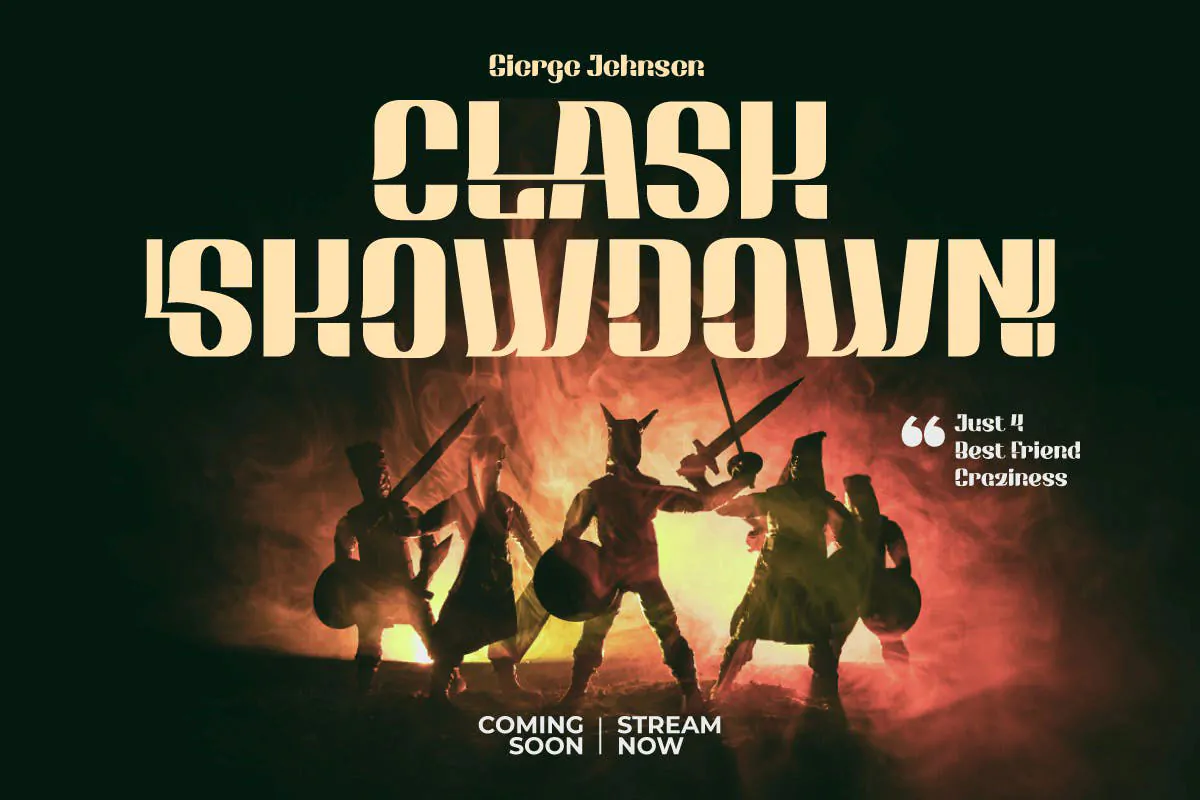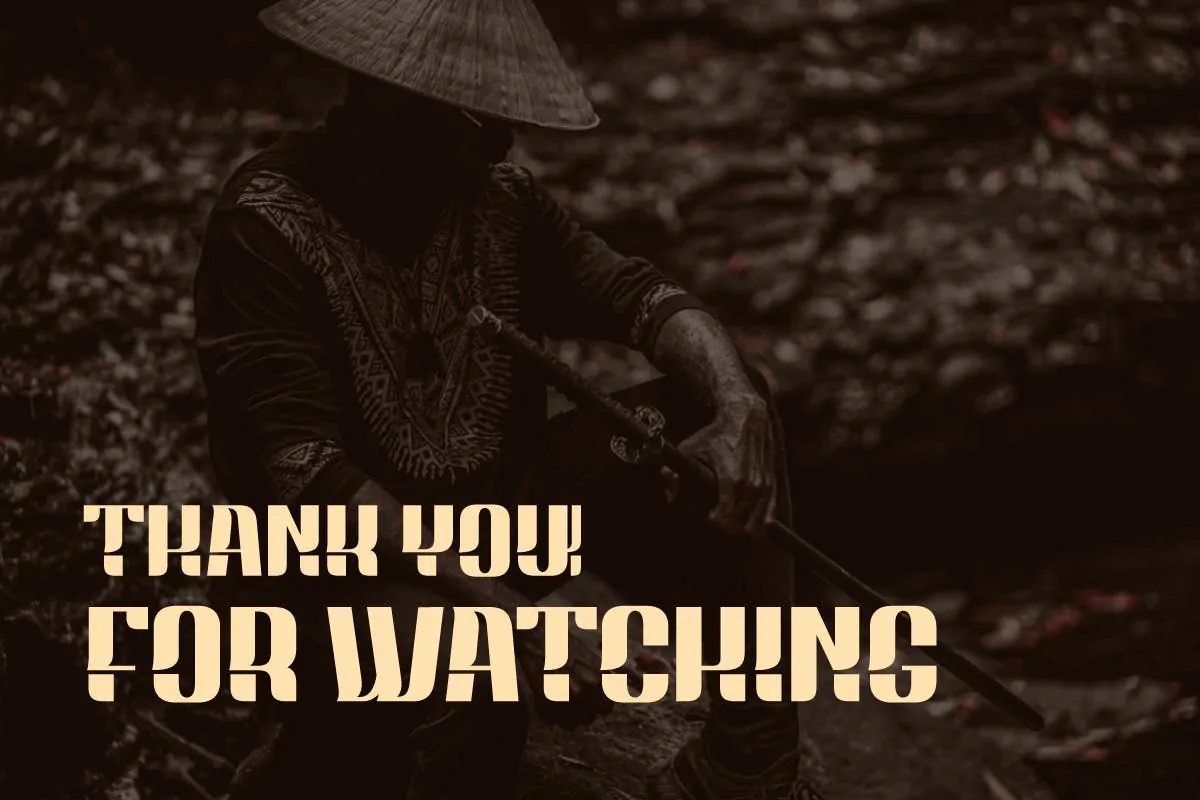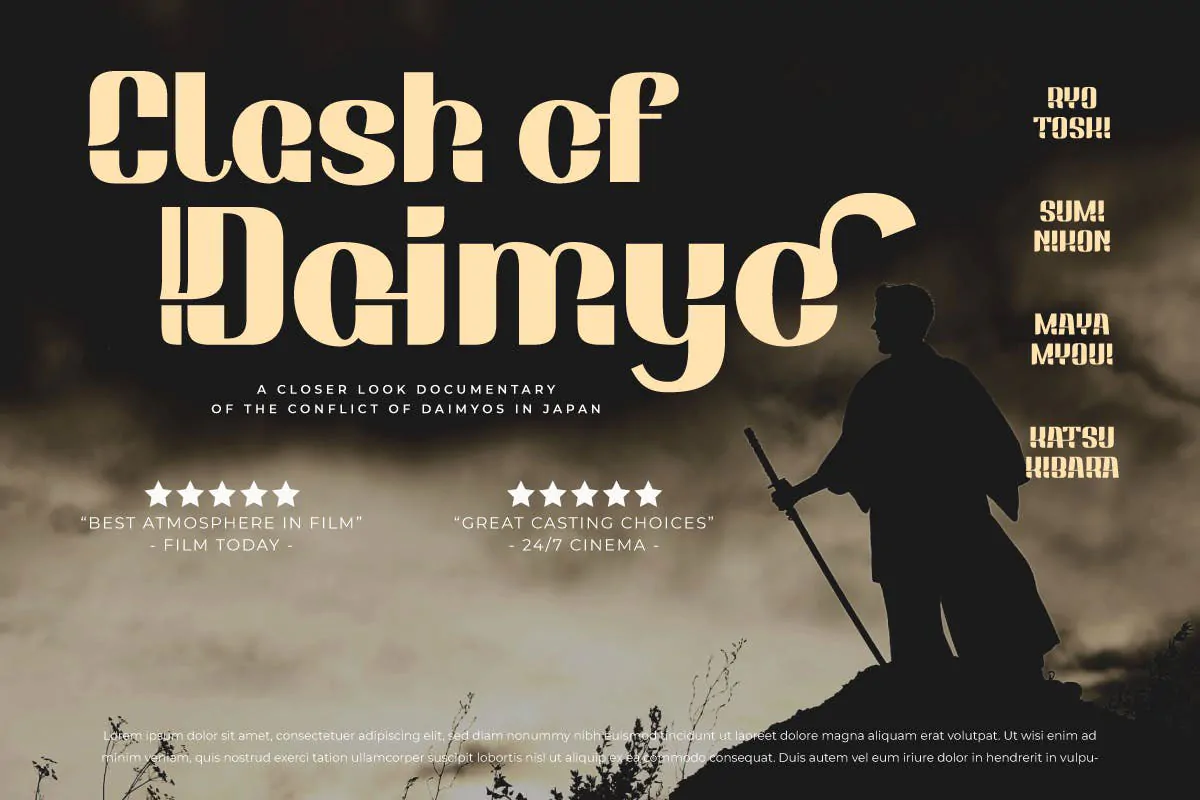
فونت انگلیسی قهرمان Ebratho
فونت انگلیسی قهرمان
فونت انگلیسی قهرمان Ebratho یک قلم زیبای نمایشی است که مناسب برای استفاده در طراحی پوستر، بنرف کارت ویزیت، مجلات، بسته بندی محصولات، کاور آلبوم موسیقی، تیشرت و … میباشد.